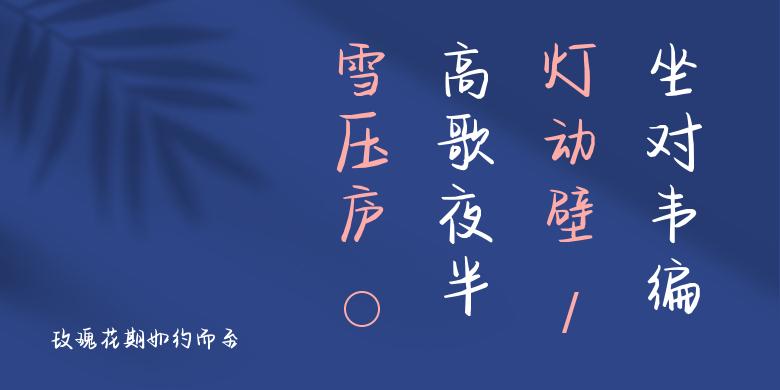
玫瑰花期如约而至
玫瑰花期如约而至,这款字体结构工整、笔画清晰,兼顾美观与易读性,适用于标题、正文、海报、包装、LOGO 等多种场景。字形优雅稳定,风格百搭耐看,适配日常排版与创意设计,让文字呈现更舒适、更具质感。玫瑰花期如约而至一笔一画,皆是细节,以均衡的比例、流畅的线条打造舒适视觉体验,字形端正大气,风格简约现代。无论是商业设计、品牌宣传还是日常排版,都能轻松驾驭,让文字更有格调与力量。玫瑰花期如约而至字体下载。